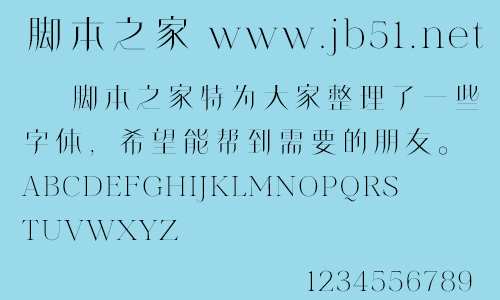
方正飄體簡ExtraLight 是方正字庫最新開發(fā)的中文字體,正如它的名字一樣,這款字體整體有種飄忽不定的感覺,每一個字體的筆畫都會有一筆是很淺的,猶如微風(fēng)緩緩吹來之感,適合應(yīng)用于藝術(shù)設(shè)計、平面宣傳設(shè)計、網(wǎng)頁設(shè)計等領(lǐng)域,需要的朋友可以前來本站下載。